中国风设计不会做?先从选择中国风字体开始
在这些年来中国风是比较流行的设计风格,因其气势磅礴、高贵典雅、独具韵味而受到设计师的喜爱,且广泛运用于品牌、包装、电商设计。如果想设计出中国风的版面,可以从字体入手,字体选择宋体或独特的书法体。字体选对了,基本版面的风格也就带有一种典雅的氛围。其次加入有关中国风的元素及色彩,更能形成浓厚的中国韵味气息。图文编排多运用留白的方式,尝试打造一种雅致感。那么今天,我给大家分享如何设计出别具中国气质的画面,希望以下内容对您有所帮助。
01#书法体
中国书法体是中国风设计中常见的设计元素之一,也是汉字特有的艺术形式。同一个文字用不同书法来写,传递出来的意境也不同。如果书法运用得当,往往起到画龙点睛的效果。在商业设计上所使用的书法体,一般由专业的字体设计师或书法家所设计。
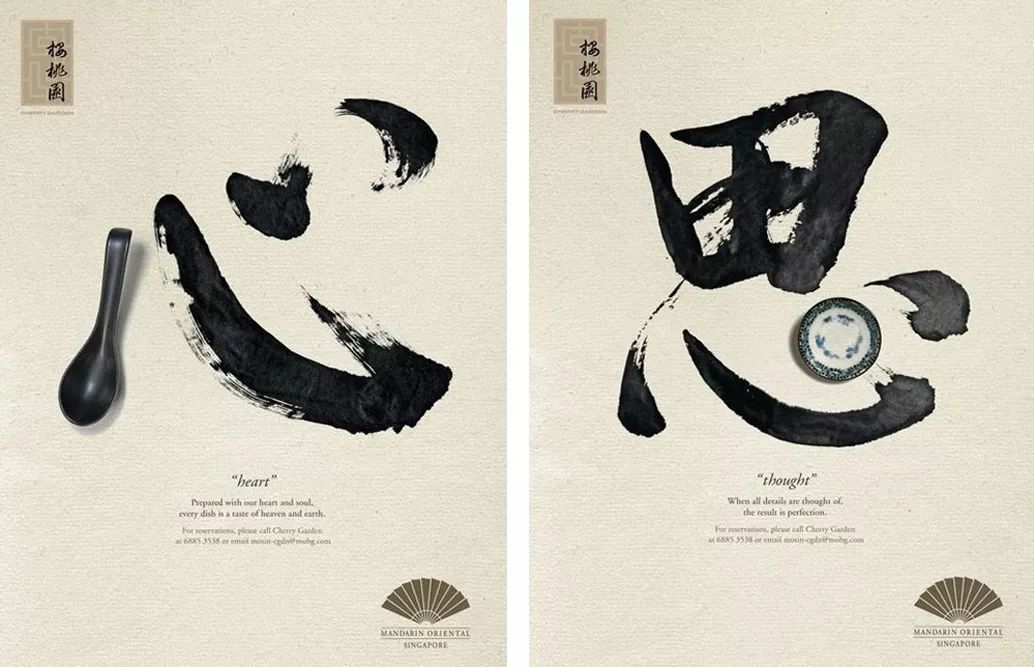
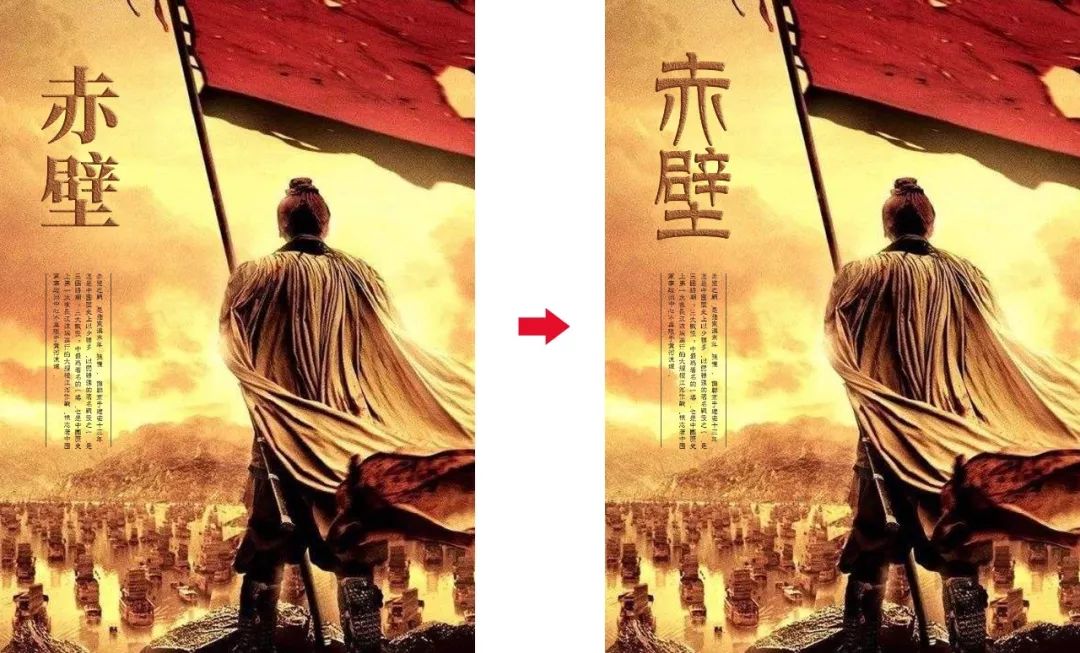
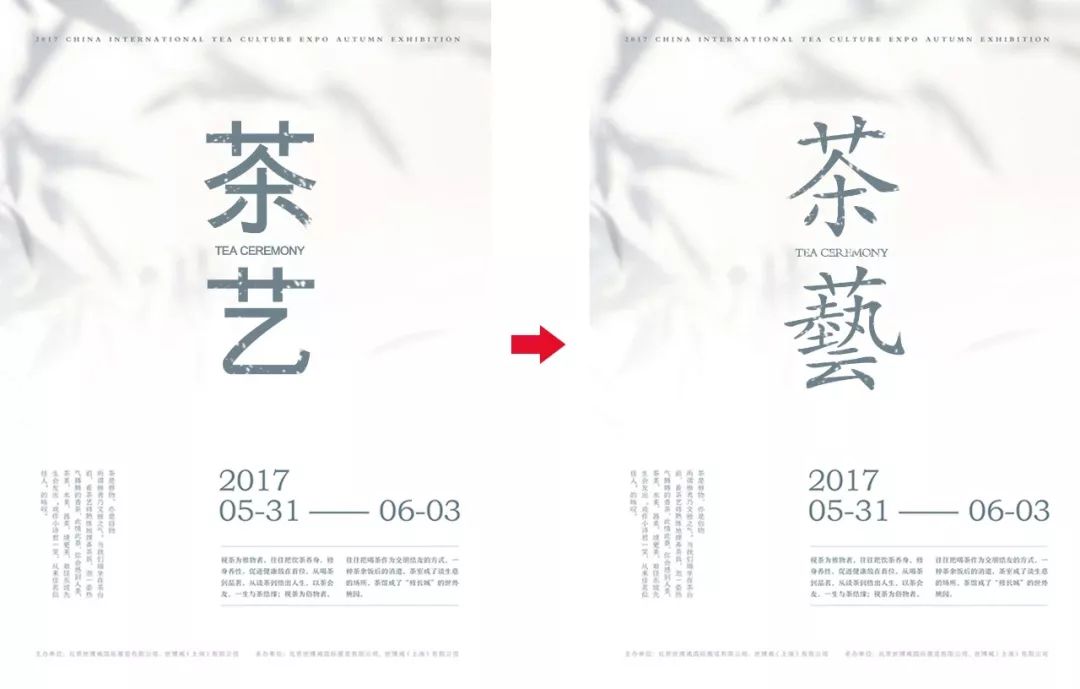中国书法主要分为篆、隶、楷、行、草五种书法体,每种书法体都有着它独特的美感和气质。
▲ 篆书:笔画造型复杂,字型瘦高、严谨秩序,给人一种古典高雅的感觉。(右图字体为方正悬针篆变简体,非免费商用字体,仅供学习)
▲ 隶书:基本由篆书演化而来,主要将篆书圆转的笔划改为方折。字形多呈宽扁,横画长而竖画短。(右图字体为方正隶变繁体,非免费商用字体,仅供学习)
▲ 楷书:又称「正楷」,字型端正清晰、易读性高,给人一种方正严谨的感觉。楷书实用性高,适用范围广。(右图字体为方正楷体繁体,非免费商用字体,仅供学习)
▲ 行书:在隶书的基础上发展起源,介于楷书、草书之间的一种字体。它不像草书那么潦草,也不像楷书那样端正。行书实用性和艺术性皆高,适用范围非常广。(右图字体为春联标准行书体,非免费商用字体,仅供学习)
▲ 草书:笔画连绵,造型极具个性。虽然草书艺术性高,但是实用性不强,一般作为标题较多。(右图字体为方正黄草简体,非免费商用字体,仅供学习)
推荐几款书法体
新蒂赵孟頫、金梅毛楷书国际码、方正启体繁体、田英章毛笔楷书、流麗行書體、淡斎行書(非免费商用字体,仅供学习)
怎样的配色方案才能体现出浓厚的中国韵味感呢?为了表现出复古典雅、怀旧的感觉,会使用一些低饱和度的颜色。但避免画面过于沉闷压抑,有时候需要一些高亮度、高饱和度的色彩进行局部的点缀,使画面变得生气勃勃。例如以下的搭配:
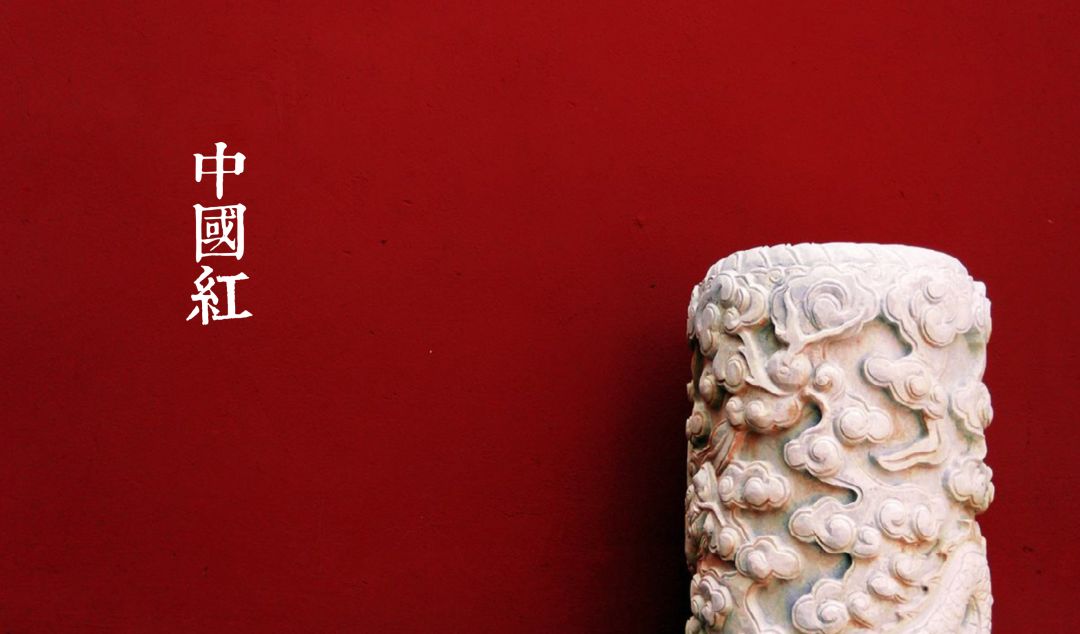
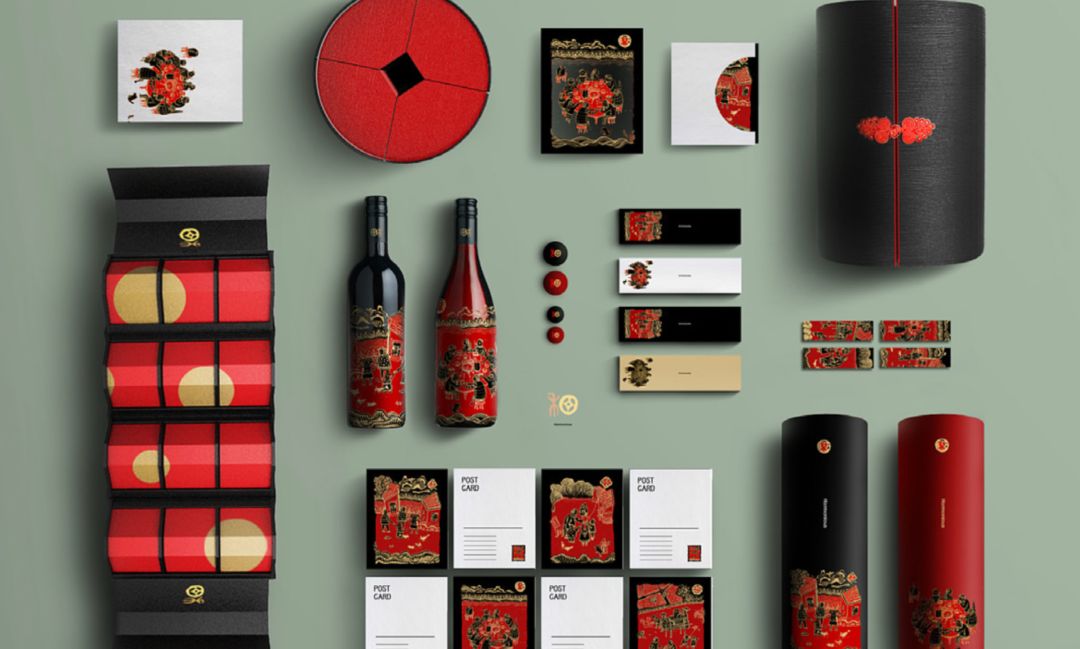
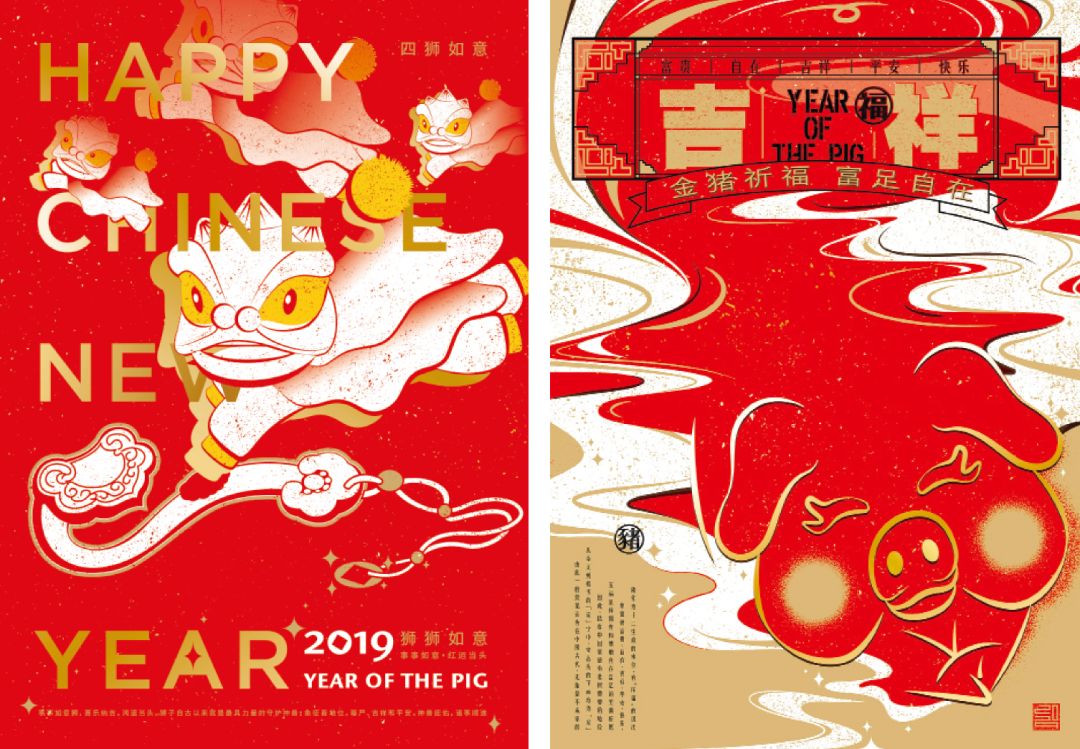红色:
例如喜庆的中国红、华贵的朱砂红、温馨的橘红等。
红黄搭配令人联想到喜庆感
黄色:
高饱和度的黄色给人高贵奢华感,相反低饱和度具有古色古香的唐韵感。不同色调的黄色调和,与红色、黑色的搭配是设计师惯用的手法。
绿色:
祖母绿指绿矿石带有莹亮光泽的深绿色,也是一种绿宝石的名称,受到皇帝贵族的喜爱。而现在的设计也经常作为中国风的配色。当然还有竹青色,也是国画中常用的颜色。
黑白灰:
如果想演绎出浓厚的书法水墨风情和简洁的中式风格,那么黑白灰的配色是个不错的选择。
蓝色:
精致淡雅的蓝色,非青花瓷莫属,而青花瓷又是中国传统元素之一。蓝白相间的配色看起来简单,却体现出雅致感。
03#水墨肌理
水墨肌理在中国风设计中运用非常广泛,具有意想不到的造型效果。肌理不仅表现出物体的质感,同时还能使画面呈现多样的视觉效果。不同的肌理对比,可以使人感受到不同的审美意蕴。总之,水墨肌理在设计上,能瞬间体现出浓厚的中国风。
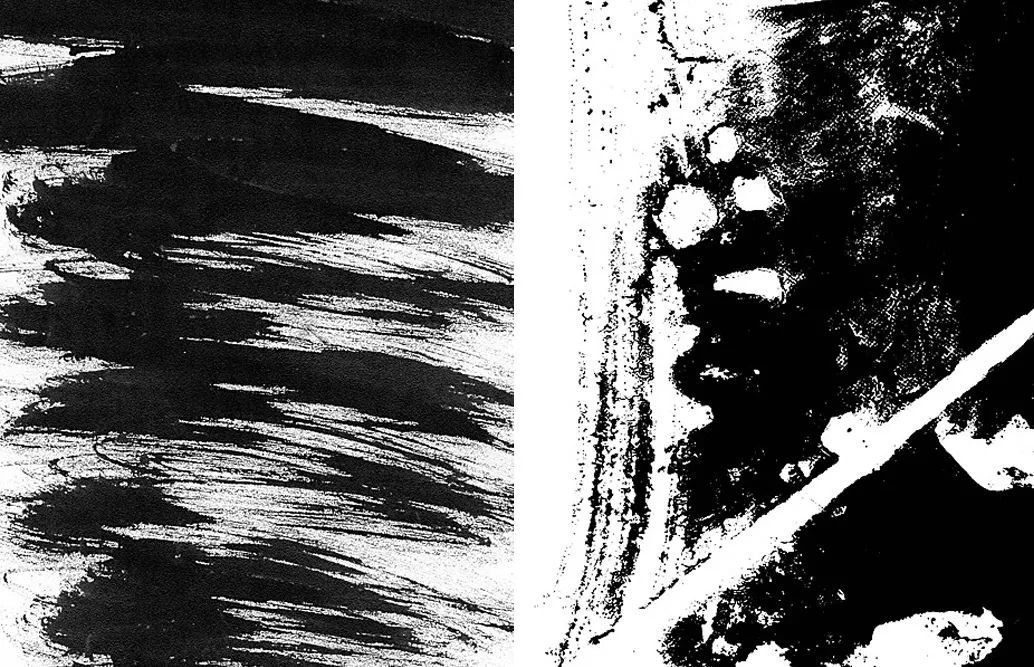
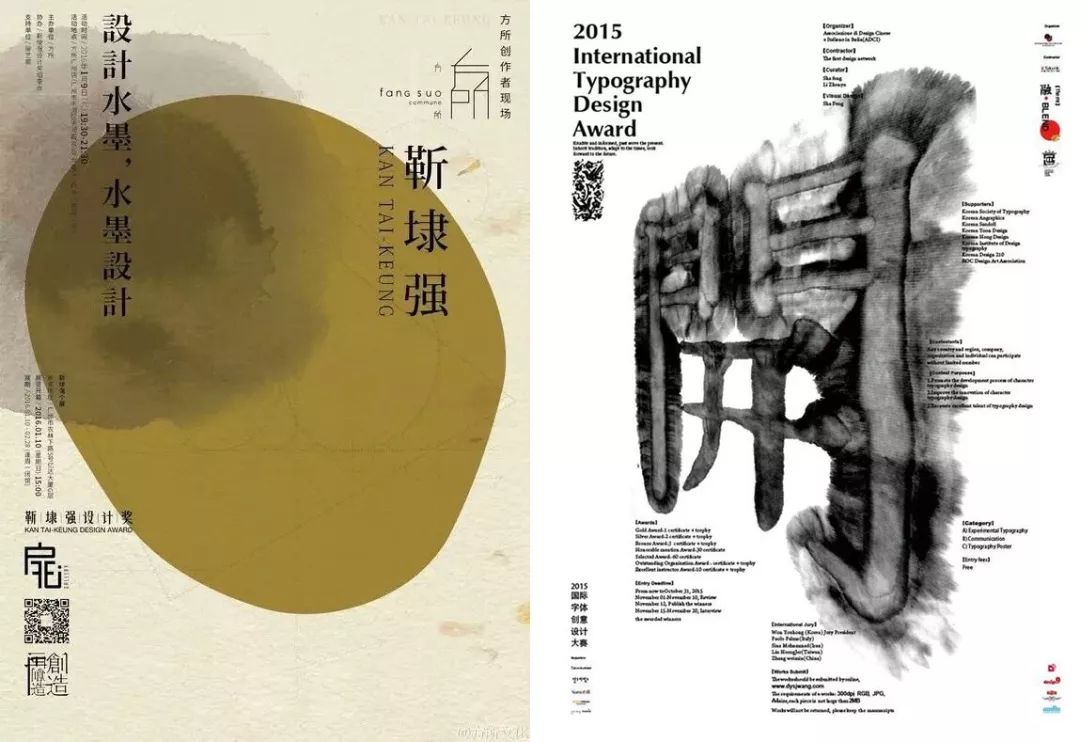
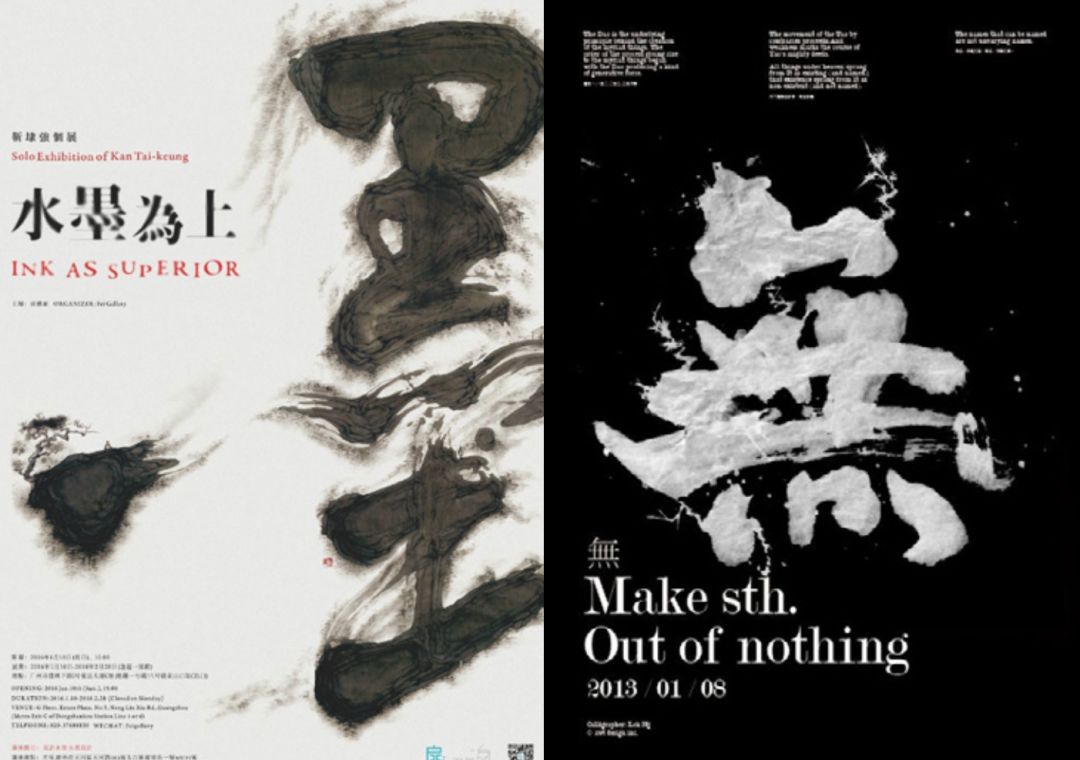
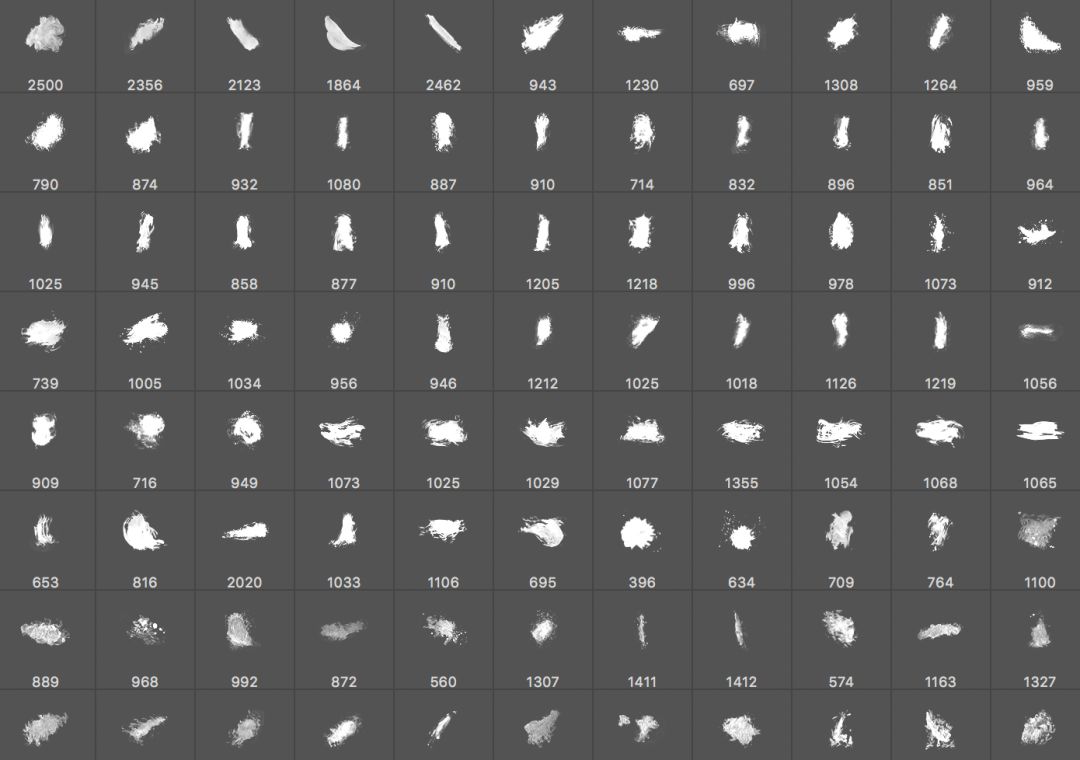
04#传统纹样
纹样作为中国传统文化的重要组成部分,一直贯穿于中国历史发展的整个流程。在我国古代文化艺术宝库中,传统图案纹样丰富多彩、璀璨夺目。添加传统纹样,能直接体现出浓厚的中国风。如果运用得当,能更加突出整个画面的氛围。
例如以下常用的纹样:
祥云纹
寓意祥瑞之云气,表达了对生命的美好向往。
如意纹
形状犹如下垂的如意,是一种典型的云纹瓷器装饰纹祥,表达“平安如意”“吉庆如意”等寓意。
曲水纹
以单朵或折枝形式的梅花或桃花,与水波浪花纹装饰。
寿字纹
古代中国传统纹饰之一。属于文字纹的一种,多施用于瓷器与布帛之上,以允装饰。
缠枝纹
以植物的枝杆或蔓藤作骨架,向上下、左右延伸,形成波线式的二方连续或四方连续,循环往复,变化无穷。
云雷纹
云雷纹是青铜器上常见的一种典型的纹饰。基本特征是以连续的“回”字形线条所构成,图案呈圆弧形卷曲或方折的回旋线条。
05#扁平写实图形
除了以上提及的水墨书法、传统纹样之外,还有其他中国元素。例如手工艺、服饰、特色食品、传统戏曲、乐器、动植物类等扁平写实图形,这些都能运用到设计当中。
▲ 扁平图形运用
▲ 写实图形运用
06#错位式标题
错位样式其实是在对齐的基础上进行位置上的改变,是一种打破常规对齐的编排布局,也是提升文字编排和整体画面创意性最简单最实用的设计技巧。
当然还有最基础的横竖编排,最初汉字是以竖向排列,从右到左的书写方式。这一特征也继续运用到设计中,竖排的布局呈现出浓烈的中国古典文化气息。
除了以上的方法可以体现古色古香的中国风之外,还能通过国画形式表达。例如水墨画、工笔画。